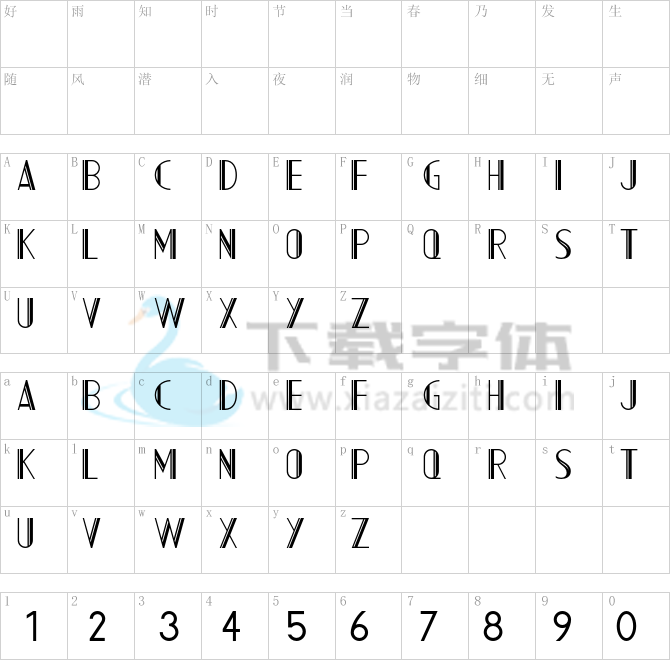
AC Mountain.otf字体下载,这款字体结构工整、笔画清晰,兼顾美观与易读性,适用于标题、正文、海报、包装、LOGO 等多种场景。字形优雅稳定,风格百搭耐看,适配日常排版与创意设计,让文字呈现更舒适、更具质感。AC Mountain.otf字体下载一笔一画,皆是细节,以均衡的比例、流畅的线条打造舒适视觉体验,字形端正大气,风格简约现代。无论是商业设计、品牌宣传还是日常排版,都能轻松驾驭,让文字更有格调与力量。AC Mountain.otf字体下载字体下载。
• 字体名称:AC Mountain